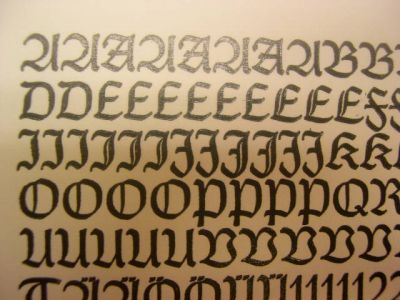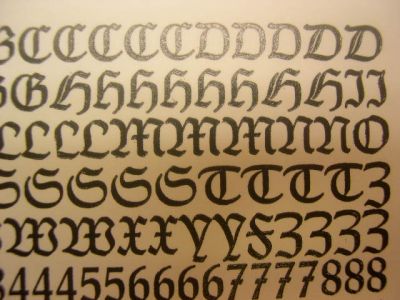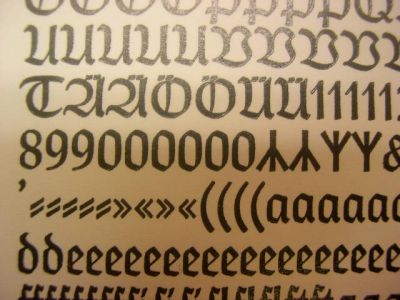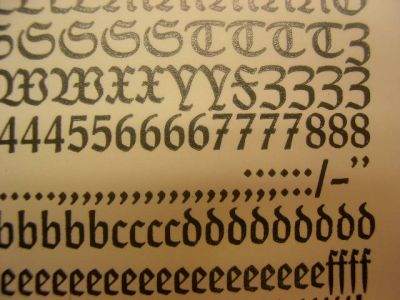
Wer kennt diese Gotische?
"Franken-Gotisch" - so soll die Schrift heißen.
Die finde ich aber nirgends.
Es gibt eine Franken-Deutsch von Alfons Schneider, Schriftgießerei Wagner, Leipzig von 1939. Davon habe ich aber leider kein Schriftmuster.
Kann mir jemand helfen?
Die Schrift ist recht einzigartig mit den zusätzlichen Schmuck-Versalien.
Bestätigt:
Dies ist eine Franken-Deutsch von Alfons Schneider, Schriftgießerei Wagner, Leipzig von 1939.